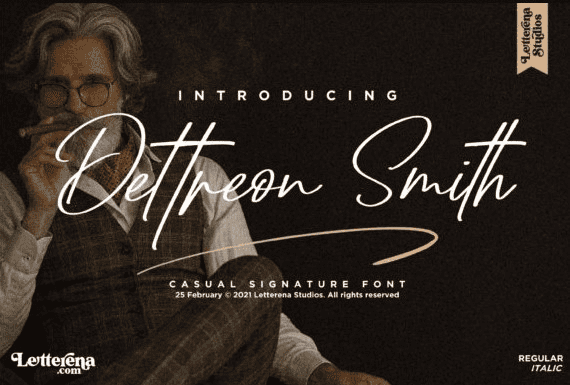
Название: Dattreon Smith Font
Dettreon Smith - красивый легкий рукописный шрифт с уникальным ощущением и потрясающим воздействием.
Он добавит роскошную искру в любой дизайнерский проект, который вы хотите создать!